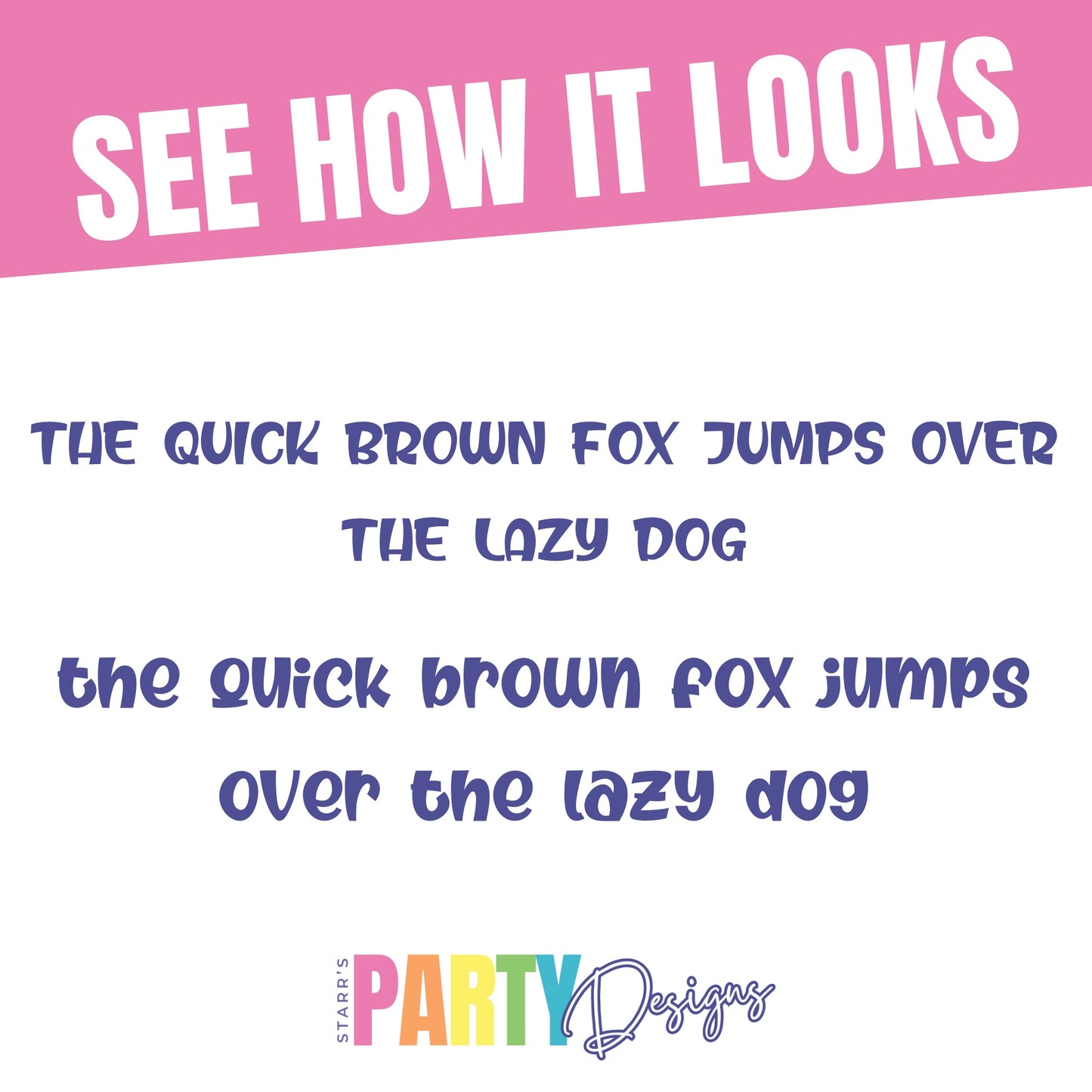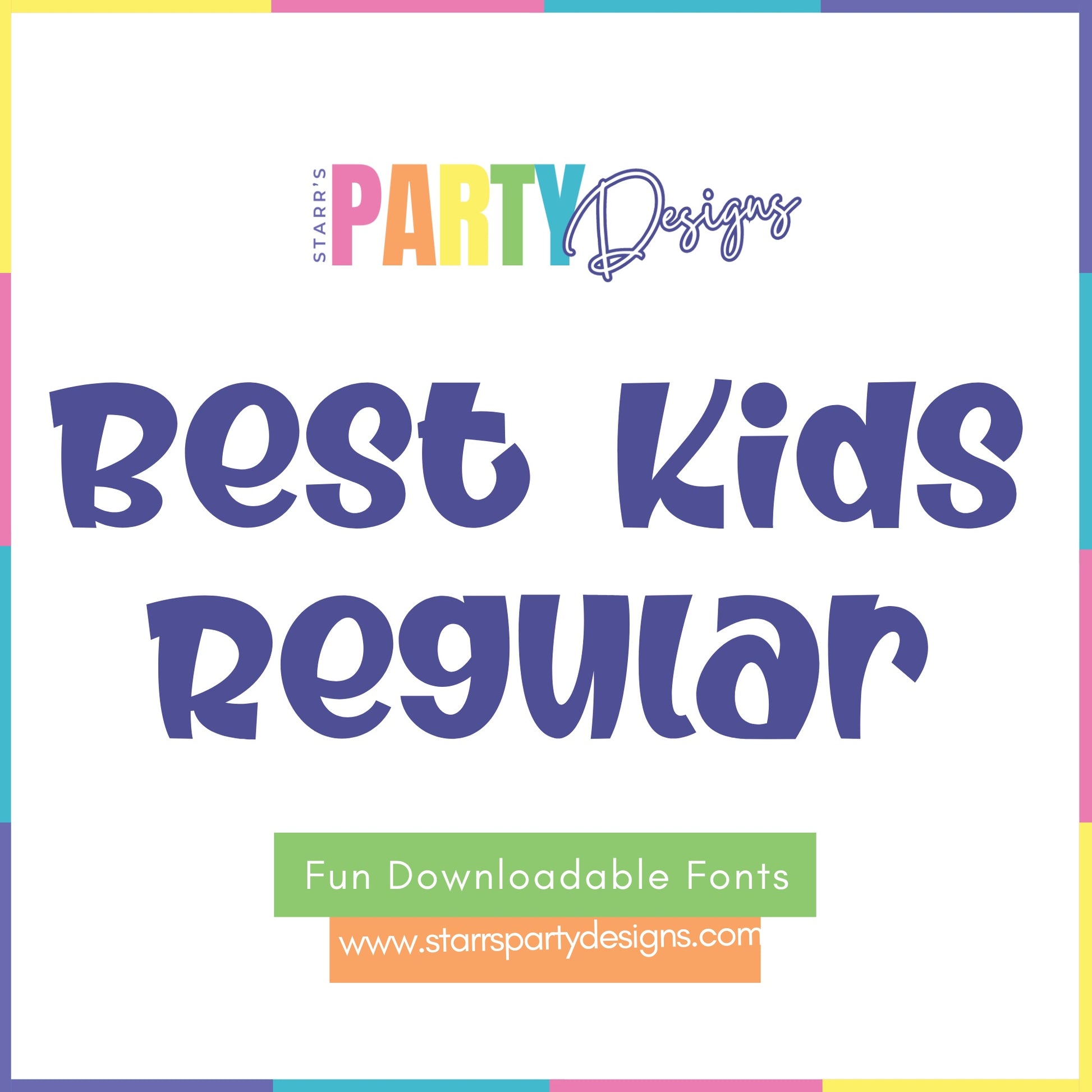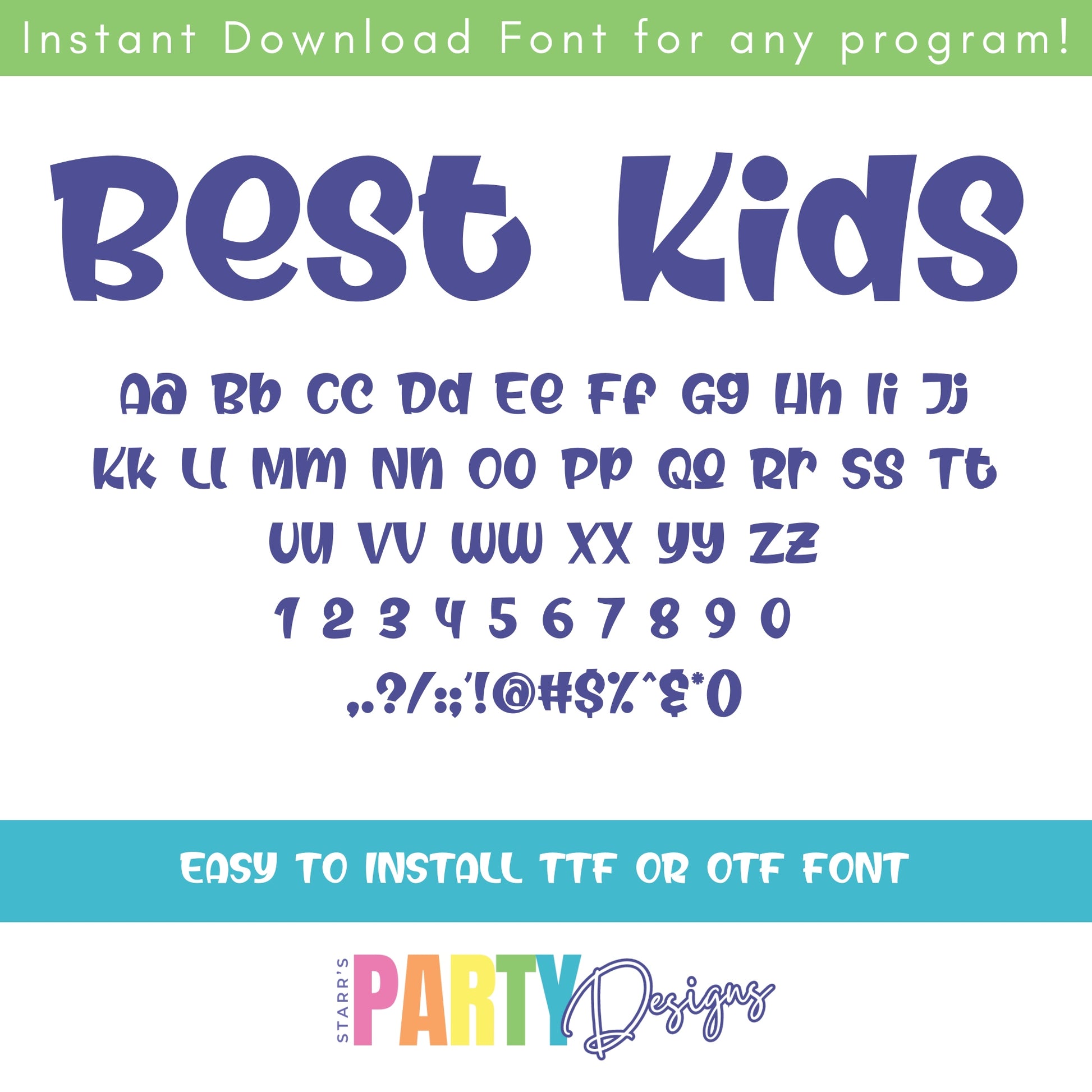
LA MEJOR FUENTE REGULAR PARA NIÑOS
¡La mejor fuente regular para niños es perfecta para: manualidades de diseñadores, logotipos, marcas, archivos svg, tarjetas de felicitación, Procreate, camisetas, carteles, redes sociales, impresiones de agendas y más!